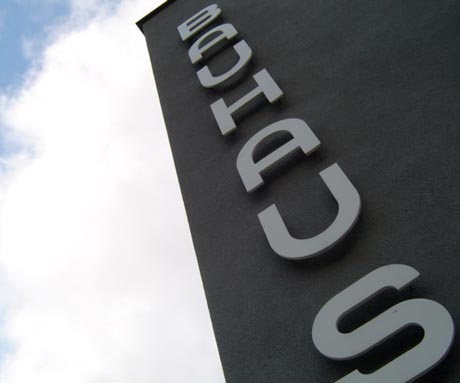
bauhaus (1919-1933)Esta famosa escola estabeleceu os conceitos do design funcionalista e da didáctica desta nova actividade. Nenhuma outra instituição teve tão forte impacto no design e na tipografia do século xx.
O design gráfico institui-se como disciplina autónoma a partir dos movimentos de arte moderna dos anos 1900-1920, vindo a consolidar-se como profissão nos anos 60. As suas bases teóricas provêm de movimentos de vanguarda, como o Construtivismo, de Stijl e a Bauhaus. A Bauhaus, escola fundada em 1919 na Alemanha, contribuiu de forma significativa para a definição do papel do design e do designer. história da bauhaus1918: As grandes rupturas depois do caosA chacina da I. Guerra Mundial é abortada em 1918 pelos sovietes de marinheiros e soldados em Hamburg e Berlim; a guerra termina com o Acordo de Paz de Brest-Litovsk, concebido por Lenin. Os artistas e intelectuais que tinham participado nos combates voltam das trincheiras com a consciência de que a guerra era a manifestação do total absurdo e da bancarrota da sociedade burguesa. Os antigos patriotas radicalizam-se; a expressão política deste radicalismo são as Räterepubliken, os sovietes alemães. No âmbito das ideologias burguesas, o movimento Dada, e depois o Surrealismo são articulações imediatas da ruptura desta geração com todos os valores estético-culturais tradicionais. 1919: A primeira etapa a Bauhaus expressionistaImplementada com a missão de promover a união entre a arte e a técnica, apresentou nos seus primeiros anos de funcionamento (etapa expressionista) uma orientação mais individualista, valorizando a expressão pessoal do artista na concepção do produto. Neste período, a escola começou a ocupar-se da produção de modelos de produtos para a indústria, consolidando a linguagem estética que caracteriza a Bauhaus até os dias de hoje, chamada por Maldonado «funcionalismo técnico- formalista». 1923: Os funcionalistas marcam o novo rumoSob a pressão de Gropius, o esotérico Johannes Itten é levado a abandonar o Grundkurs; o artista húngaro László Moholy-Nagy passa a ser o novo docente deste curso. Neste «Curso Básico», também deram aulas Wassily Kandinsky, Paul Klee e Josef Albers. A influência do movimento de vanguarda holandês De Stijl e o vitalismo do Suprematismo e do Construtivismo da vanguarda soviética russa marcam a estética geral e a tipografia professa dentro da Bauhaus. O De Stijl foi um movimento de arte que enaltecia o controle racional do processo criativo apropriando-se de sua morfologia baseada nas formas elementares e nas cores primárias. Essa orientação estética vinha ao encontro dos interesses da Bauhaus em estreitar o seu relacionamento com a indústria, com a produção em massa e com o emprego de máquinas. Moholy-Nagy entra na Bauhaus em 1923. Nos seus manifestos, o conceito de uma nova tipografia («neue typographie») ocupava um papel central. «die neue typographie» foi o título programático de um artigo de Moholy-Nagy, publicado já em 1923 no bauhausbuch artigo que articulou ideias essenciais; pouco depois, Jan Tschichold faz ressonância às teses de Moholy-Nagy, ampliando a sua divulgação. Em 1923, é organizada a primeira exposição da Bauhaus, um esforço de promoção das ideias e práticas do instituto junto do grande público. O catálogo foi desenhado por Herbert Bayer. 1925: Mudança para DessauOs dirigentes da Bauhaus cedem à pressão da «opinião pública» e mudam a Escola para Dessau, uma cidade industrial em rápida expansão, na periferia de Berlim. |